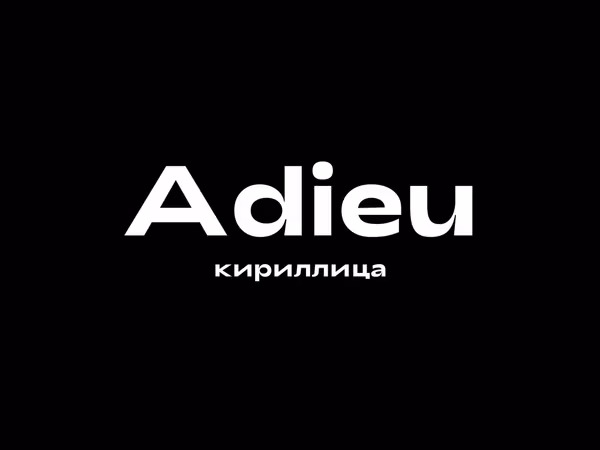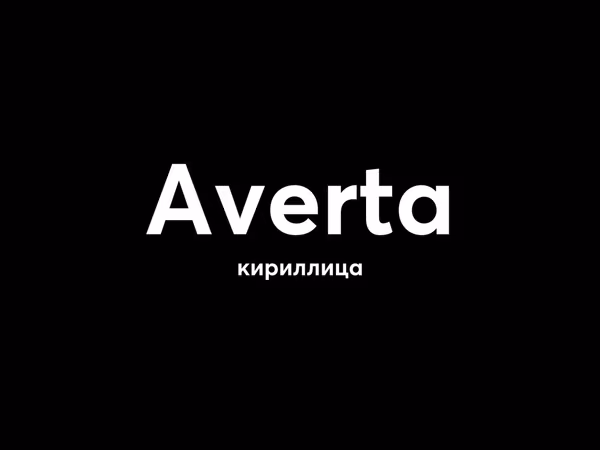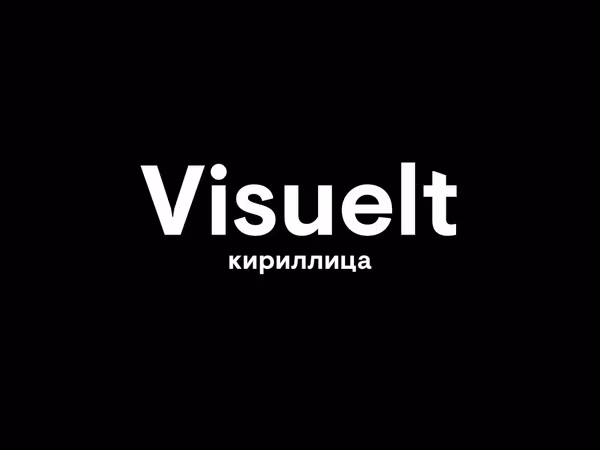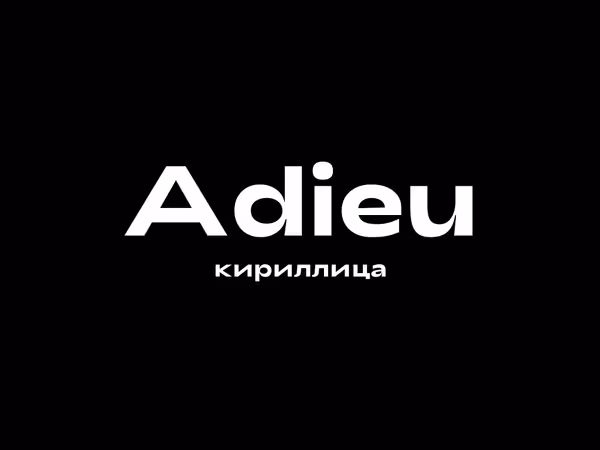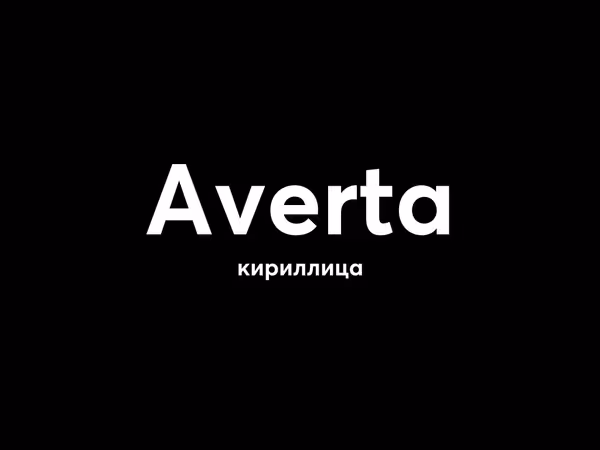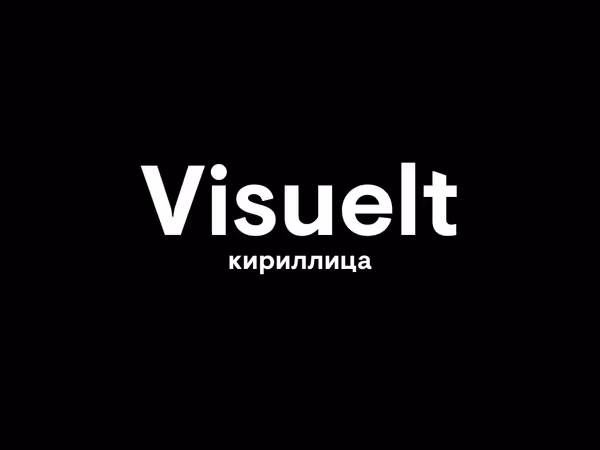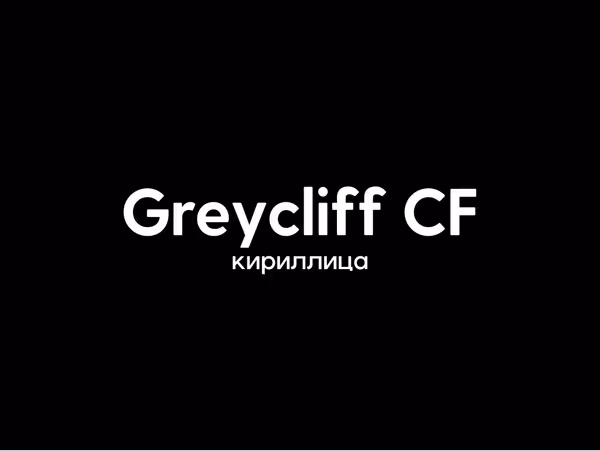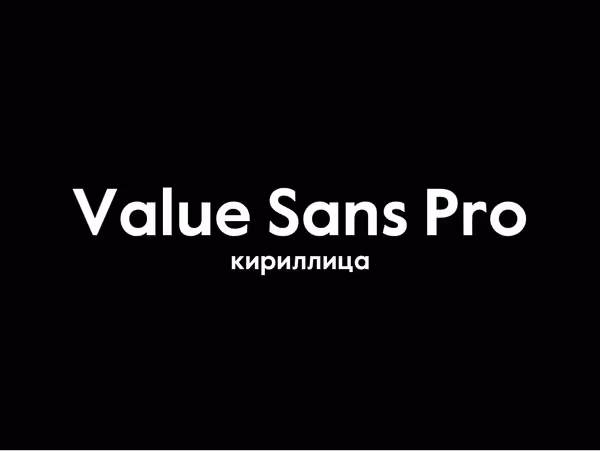
Mazzard шрифт
Кириллический шрифт Mazzard. Mazzard - это суперсемейство трех геометрических гротесков с тремя различными высотами по оси x (H, M и L).Он имеет широкую языковую поддержку, включая кириллицу, и предлагает широкий выбор альтернативных форм на выбор.
Greycliff CF шрифт
Greycliff - это универсальное семейство кириллических шрифтов. Плотные заглавные буквы и гладкие открытые строчные буквы эффективны в широком использовании. #fonts #greycliff
Value Sans Pro шрифт
Кириллический шрифт Value Sans Pro. Value Sans заимствует стиль и поведение у таких прецедентов, как Elegant Grotesk (Германия) и Granby (Великобритания) #valuesanspro #font
Visuelt pro
Visuelt - это кириллический шрифт без засечек. Это очень уникальный и удивительный шрифт. Этот шрифт был разработан как индивидуальный шрифт для конференции по идентичности дизайна 2013 и 2014 годов, которая также известна как Национальная норвежская награда за дизайн.
Шрифт Adieu
Adieu - это кириллический расширенный шрифт без засечек, вдохновленный спортивной культурой и высокой скоростью. В основном он разработан для заголовков и логотипов, но его применение широко где используется.
Averta шрифт
Кириллический геометрический шрифт Averta. С поддержкой 250+ языков.